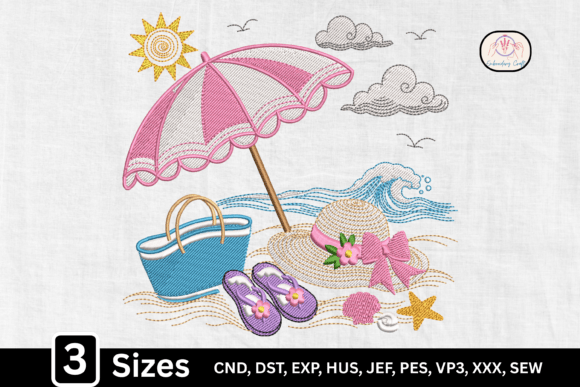
Coastal Summer Beach Vacation
Att hitta rätt designelement kan vara utmanande, men Coastal Summer Beach Vacation erbjuder en exceptionell samling som omedelbart lyfter ditt arbete.
Oavsett om du skapar POD-produkter (Print on Demand), bröllopsinbjudningar eller grafik för sociala medier, är Coastal Summer Beach Vacation ett perfekt val.